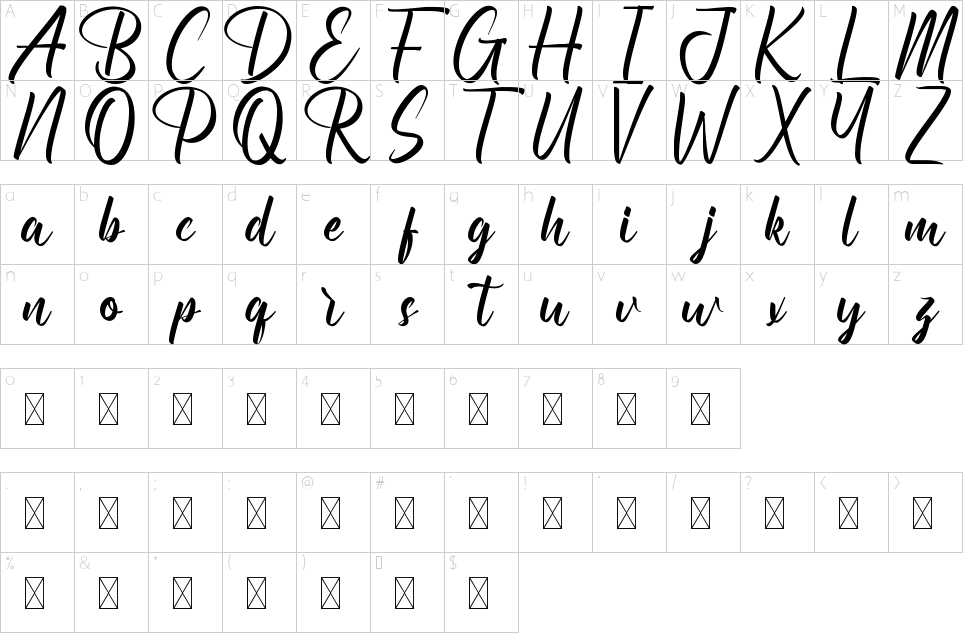
Aqui está uma descrição criada em português do Brasil para a página de download da fonte ‘Dreamking Font’: Descubra agora a ‘Dreamking Font’, uma das últimas adições à categoria gratuita na nossa seletiva seleção de fontes digitais. Desenvolvida pelo designer independente RaisProject, esta elegante e versátil fonte pode ser utilizada em Windows ou Mac para dar um toque único aos seus documentos e projetos. Com seu design sofisticado e fácil de ler, a ‘Dreamking Font’ é perfeita para estilos de escrita distintivos que buscam uma identidade única e moderna. Seja você criador de conteúdo digital, designer gráfico ou qualquer profissional da área do design, essa fonte será um complemento indispensável à sua biblioteca de ferramentas. Recentemente, a ‘Dreamking Font’ já foi baixada mais de 1.880 vezes por nossos usuários, o que mostra não apenas seu valor como recurso gráfico, mas também sua aderência às necessidades e requisitos das comunidades de design atualmente. Se você está buscando uma fonte moderna e estilizada para dar um gás à sua próxima produção visual, ‘Dreamking Font’ é a escolha perfeita.